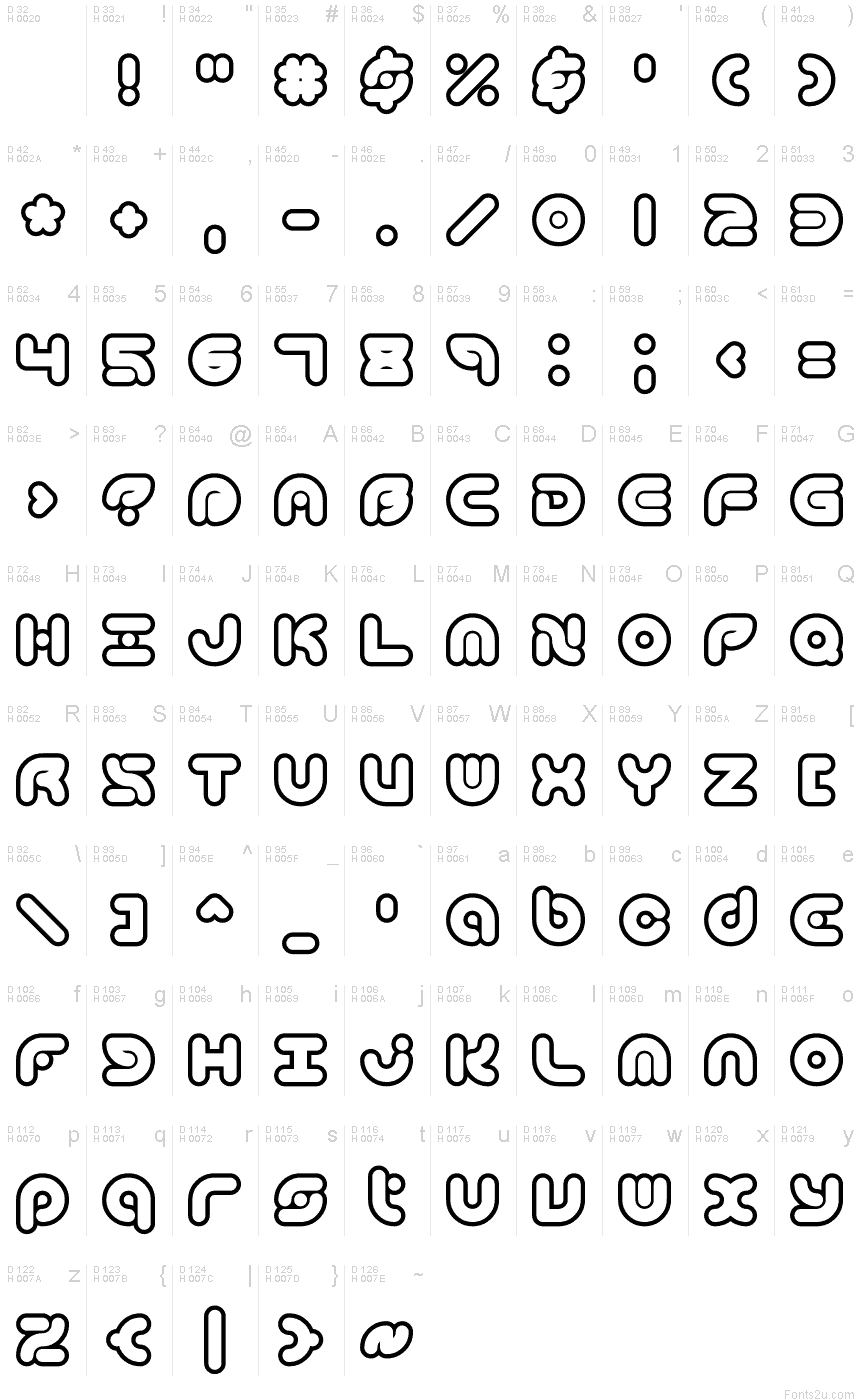
Technique OL di AEnigma Fonts è un font display gratuito dallo stile groovy, con un morbido richiamo agli anni '70. Le lettere sono grandi, rotonde e gonfie, con contorni spessi e forme interne semplici che rendono il carattere amichevole, morbido e quasi giocoso, evitando spigoli duri.
È adatto a poster, bozze di loghi, packaging, flyer musicali e cartoline creative dove serve un tono retro deciso per frasi brevi, senza risultare troppo elaborato. Essendo un font gratuito, è perfetto anche per copertine e monogrammi: i contorni spessi e le curve corpose mantengono le lettere graficamente incisive anche quando il testo è breve.